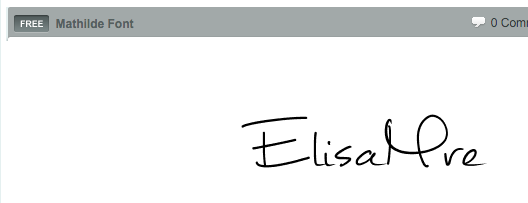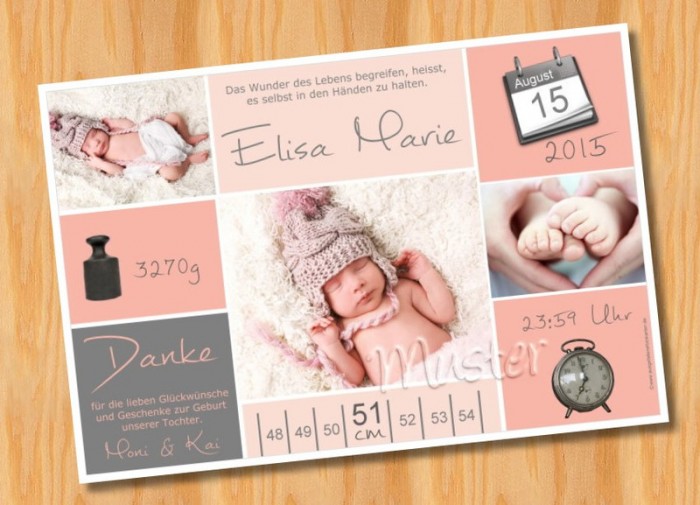
Erkennt jemand diese Schriftart?
ich suche noch eine weitere Schriftart - wieder von einer Babykarte. Kann mir jemand weiterhelfen? Es soll die, die nach Handschrift aussieht sein. ;-) Das wäre toll...